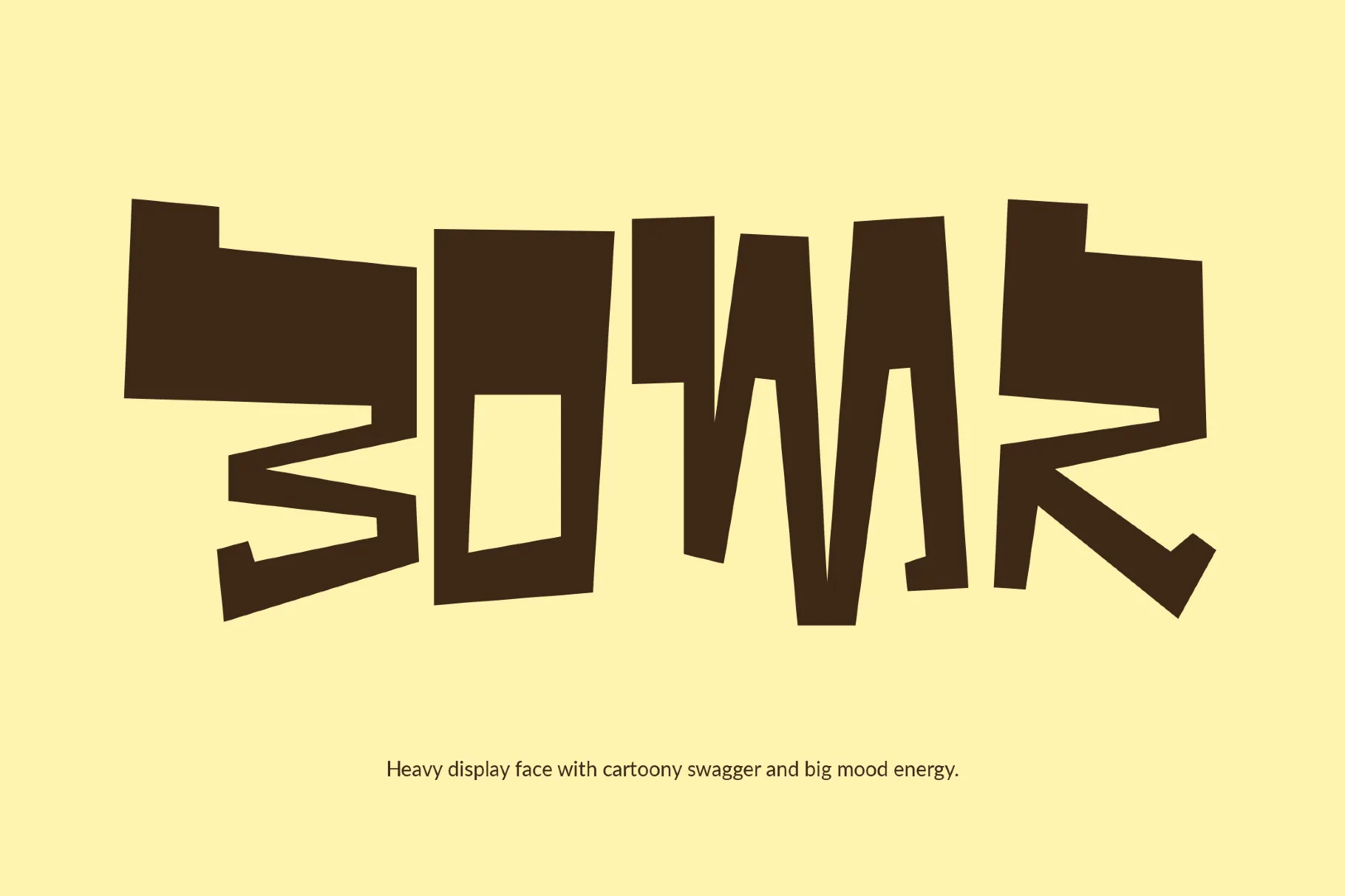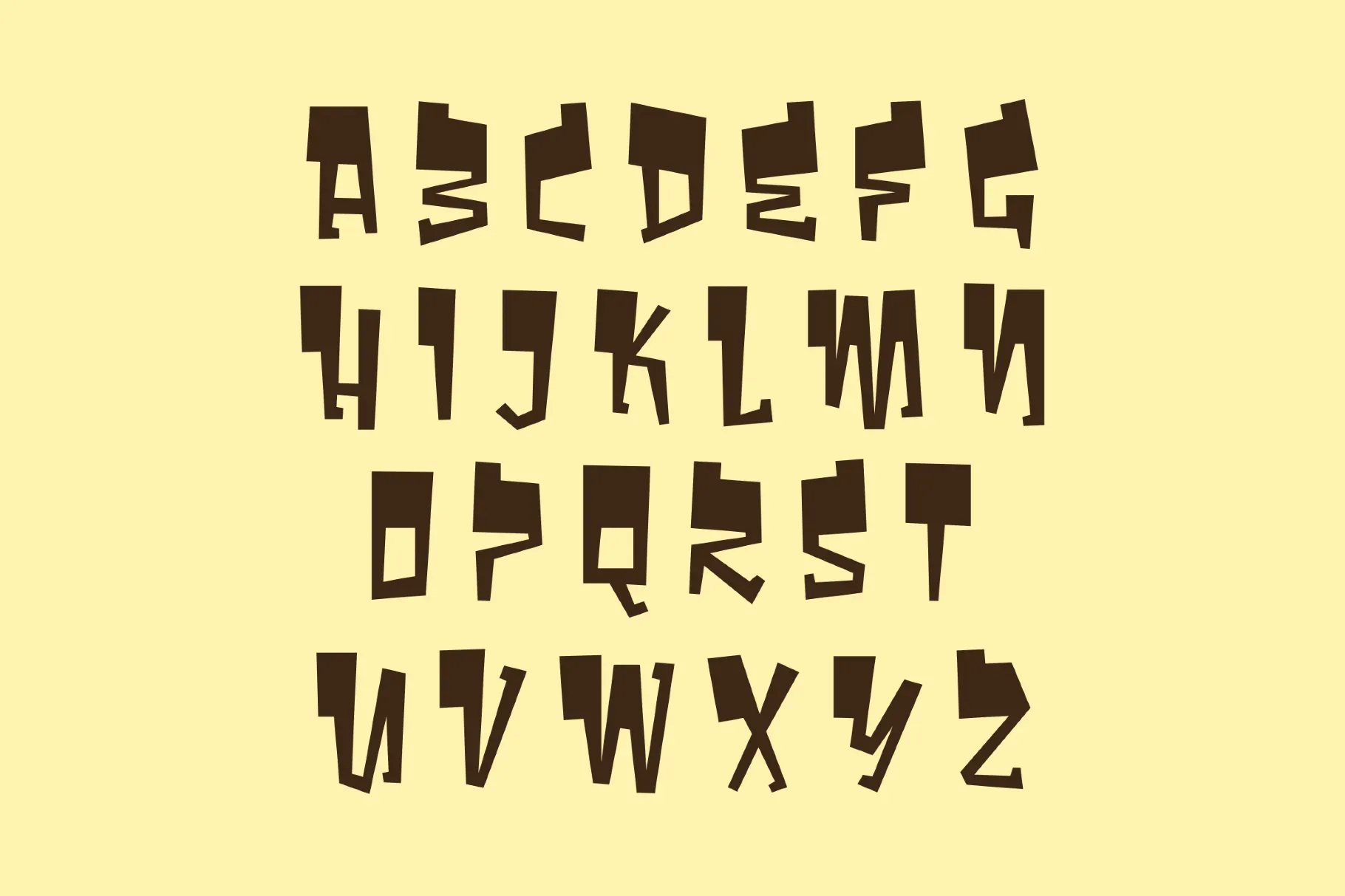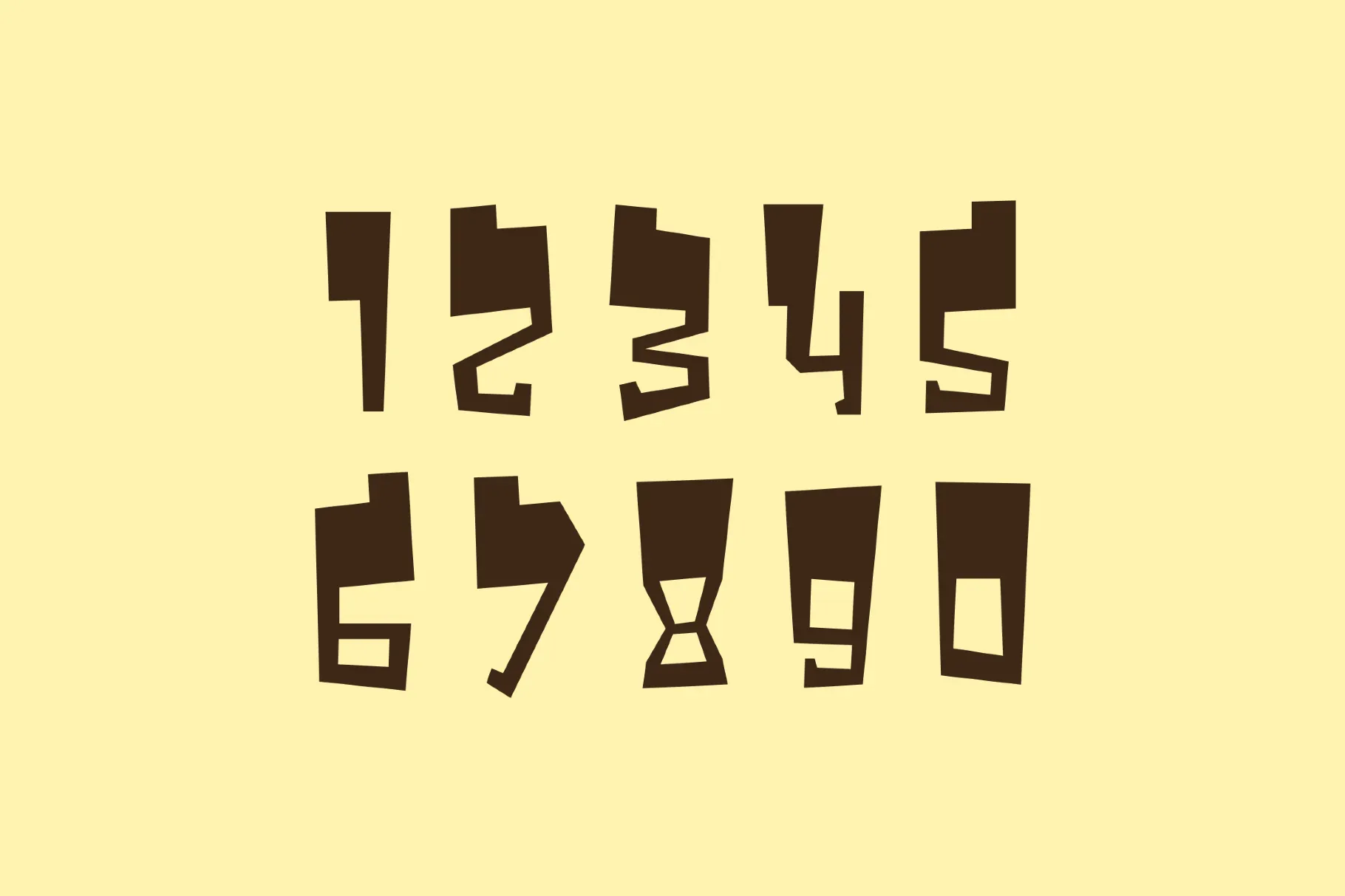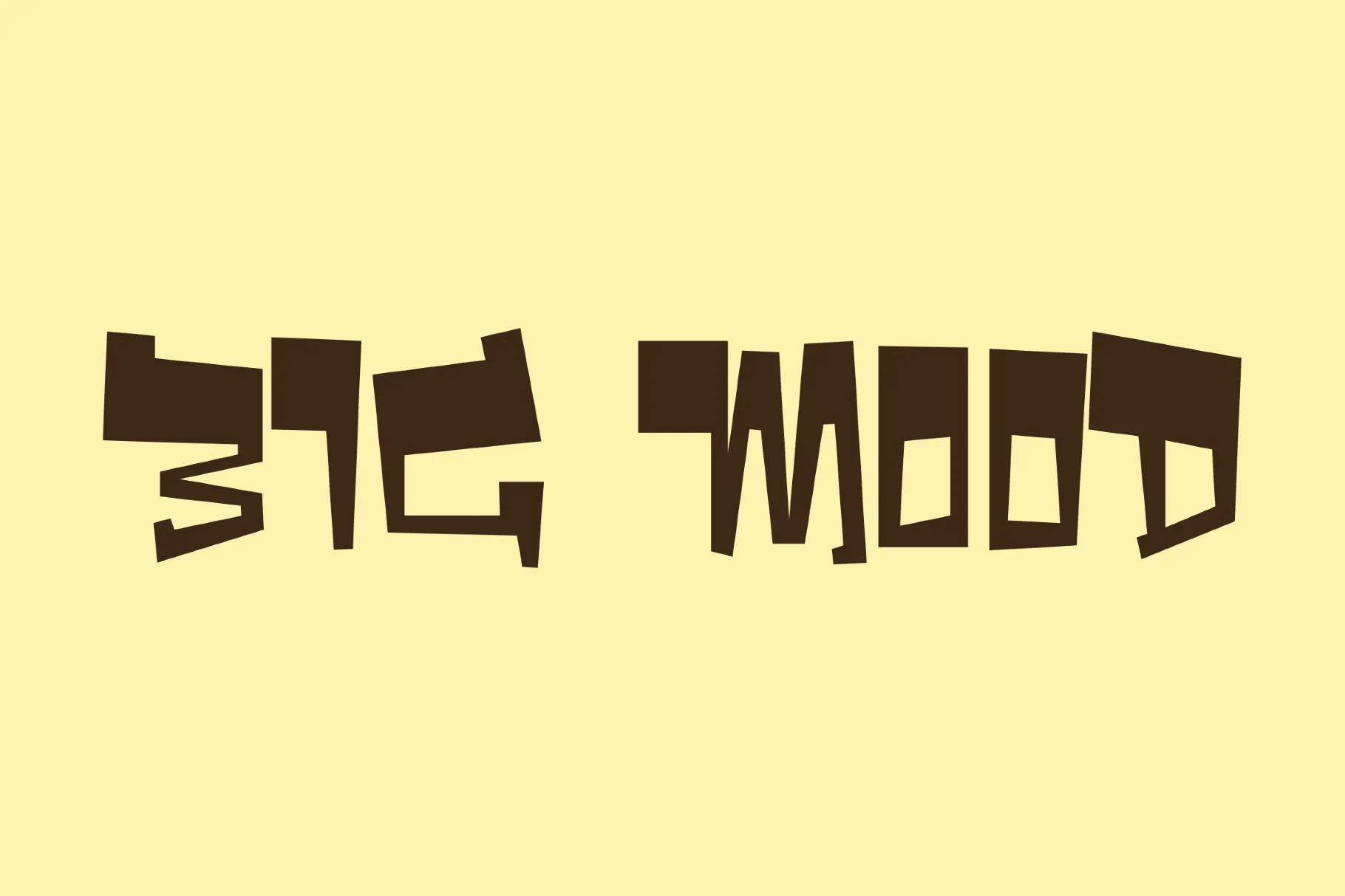
Bombr
Bomr 是一款具有强烈手工感与趣味性的西文展示字体,整体设计以“剪纸”与“纸板切割”为视觉灵感,将字母拆解为富有几何感的块面结构,并通过不规则的轮廓、错落的比例以及略显粗粝的边缘,形成独特而轻松的视觉效果。与传统几何字体追求严谨、规整的字形不同,Bomr 更强调手工制作所带来的自然变化,使文字呈现出鲜明的个性与玩味。
从字形表现来看,Bomr 采用厚重的块面造型,字母内部保留较为明显的留白与切割结构,同时刻意加入倾斜、错位、缺口以及不对称的几何变化,让每个字符都具有较强的辨识度。部分字母的笔画呈现出类似纸片拼接或纸板镂空的效果,在保持整体视觉统一的同时,又赋予字体一种略带“粗野”与童趣的手工气质。
Bomr 的视觉风格还带有一定的复古设计特征,可以联想到中世纪现代主义拼贴海报、民俗手工招牌以及纸板模板字等设计形式。厚重的字面与富有节奏感的不规则轮廓结合,使字体在大字号使用时具有非常突出的视觉冲击力,尤其适合需要强调个性、趣味和艺术氛围的标题设计。
在实际应用中,Bomr 更适合作为展示型字体使用,可用于海报标题、包装设计、专辑封面、编辑类标题、品牌标识、展览视觉以及各类宣传图形等场景。其独特的几何切割感能够快速形成视觉焦点,用于短标题或品牌名称时尤其醒目;搭配简洁的版式和大面积留白,也能够进一步突出字体本身的造型特点。
在字符方面,Bomr 包含大写与小写英文字母,同时提供数字、标点符号及常用符号,能够满足英文标题、数字信息以及基础西文排版需求。由于其本身属于偏展示性的字体,因此更推荐在较大的字号下使用,以充分展现其不规则几何结构和富有手工感的字形细节。
总体而言,Bomr 并不是一款强调传统排版秩序的常规西文字体,而是将剪纸、拼贴与几何图形语言融入字母设计,通过夸张的块面、锋利的切角和不规则的字形变化,营造出轻松、复古且富有实验性的视觉气质。对于海报、包装、品牌视觉以及艺术类设计而言,它能够为文字带来更加鲜明的造型感和手工温度。